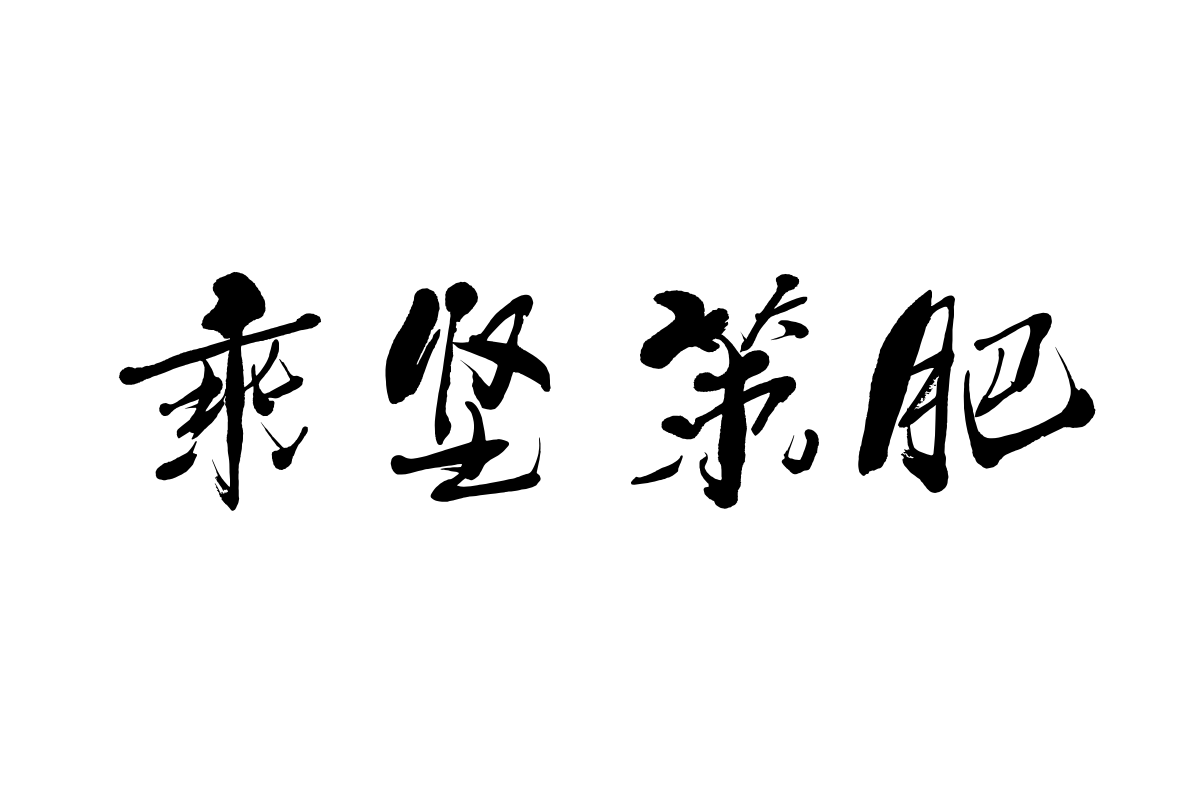
汉仪SIJIA体W是一款具有独特风格的中文字体。它源自于中国传统书法,融合了现代设计理念,呈现出一种独特的视觉美感。这款字体的特点是笔画流畅、结构紧凑,既有传统书法的韵味,又不失现代感。
在设计上,汉仪SIJIA体W采用了简洁明了的线条,使得文字更加清晰易读。同时,它的字形大小适中,既适合用于标题和正文,也适合用于各种排版设计。此外,这款字体还具有一定的艺术性,可以通过不同的字号和排版方式展现出不同的视觉效果。
总的来说,汉仪SIJIA体W是一款非常适合用于各类设计场景的中文字体。无论是用于网页设计、平面设计还是其他创意项目,它都能为你的作品增添一份独特的魅力。